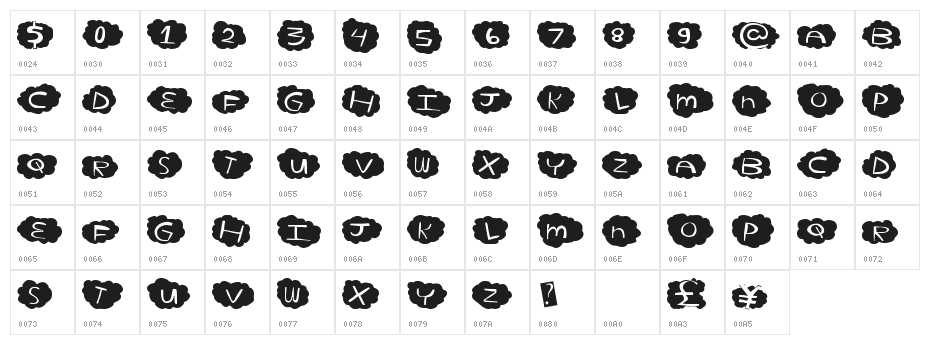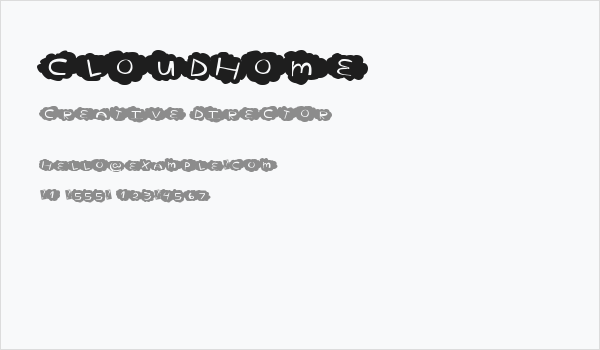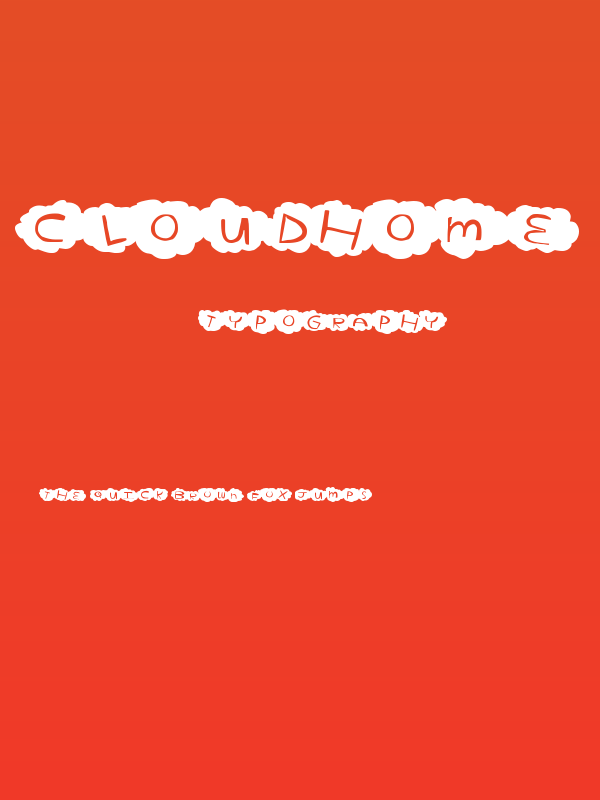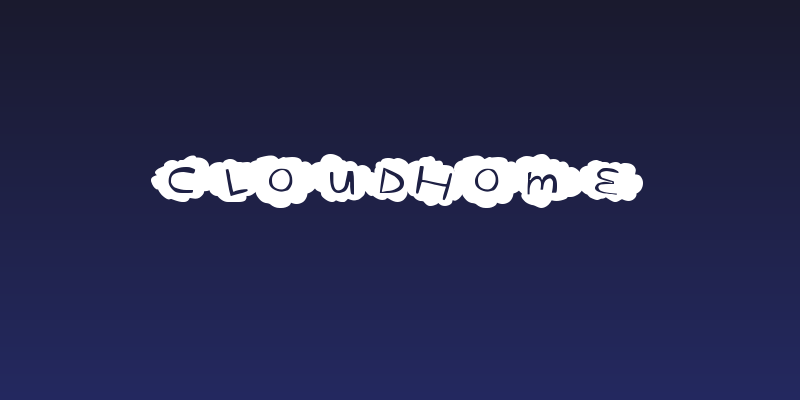
CloudHome Font
| Anwendungsfall | Logos, Headlines, Posters |
| Vorgeschlagene Projekte | Ideal for children's books, playful branding, party invitations, and creative posters. |